TWICE 演唱會顏色怎麼搭?|應援色號、推薦字體補包,讓 IG 限動質感爆棚!
每次看 TWICE 演唱會都想發 IG 限動留下美好的紀念嗎?想要讓你的 TWICE 應援照片脫穎而出,選對配色與字體就是關鍵!這次筆編為各位 ONCE 整理了最完整的應援補包,包含 TWICE 顏色官方色號、成員專屬色,以及最適合搭配的中文及英文字體推薦,跟著我們一起打造 TWICE 應援質感美照!
一、TWICE 演唱會應援|推薦搭配顏色及色號
想要製作最有「本命感」的應援圖,第一步就是精準掌握 TWICE 顏色
(一)TWICE 官方應援色
TWICE 最經典的代表色是選用杏桃色和螢光洋紅色,象徵著成員們的清新與熱情:
Pantone 712C:#FCC89B (杏桃色)
Pantone 812C:#FF5FA2 (螢光洋紅色)
(二)《THIS IS FOR》巡迴演唱會視覺色
這次睽違十年終於來台灣《THIS IS FOR》演唱會主視覺轉向深邃且充滿質感的寶藍色系,推薦大家在製作限動時,可以搭配以下色號:
主視覺深藍:#0542D2
沈穩靛藍:#062A99
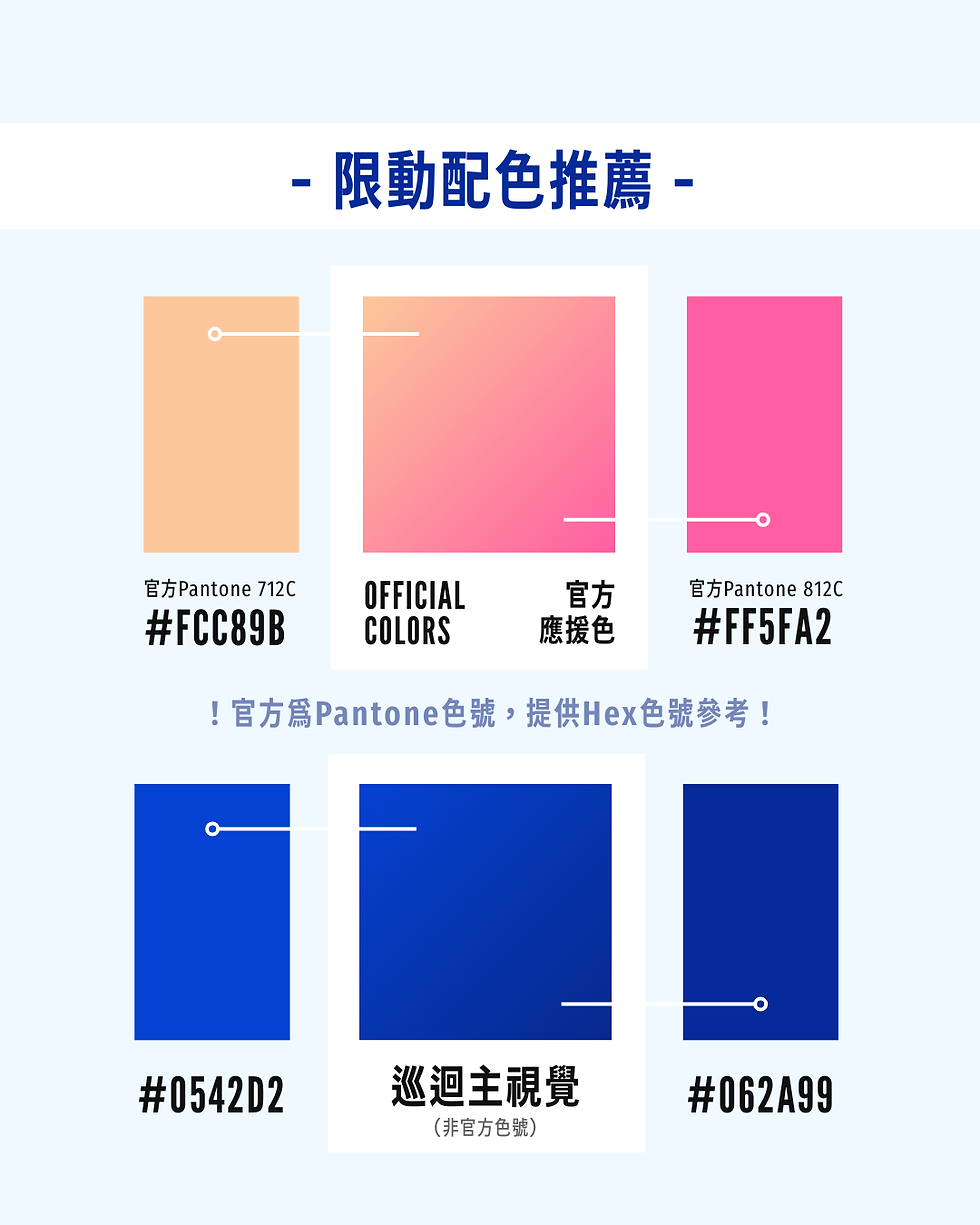
二、TWICE 九位成員專屬應援色號
如果你想要為 TWICE 個別成員應援,官方其實也有針對 9 位成員設定不同的應援代表色哦!
三、TWICE 演唱會限動字體推薦:打造精美應援視覺
選好了你喜歡的 TWICE 顏色,接下來要搭配合適的字體,才能更呈現出質感,以及演唱會充滿張力與感動的氛圍,下方提供你推薦搭配的三款英文字體與兩款中文字體!
(一)免費英文字體推薦下載
DIN Condensed
經典工業風縮體,線條俐落、排版顯得非常高級,適合用於細節資訊
Anton
筆畫厚實、極具視覺衝擊力,適合寫放大的「TWICE」或歌曲主標題
League Gothic
窄版修長設計,充滿復古美式海報感,適合標註演唱會日期、城市或成員英文名
(二)免費中文字體推薦下載
未來熒黑
結構開放且現代感十足,在手機螢幕上閱讀也清楚舒適,適合中文標題,或寫下應援的感性口號
寒蟬端黑體
字體圓潤飽滿且端正,給人溫暖且踏實的感受,適合放在照片留白處,紀錄演唱會當下的心情文字或歌詞等內文